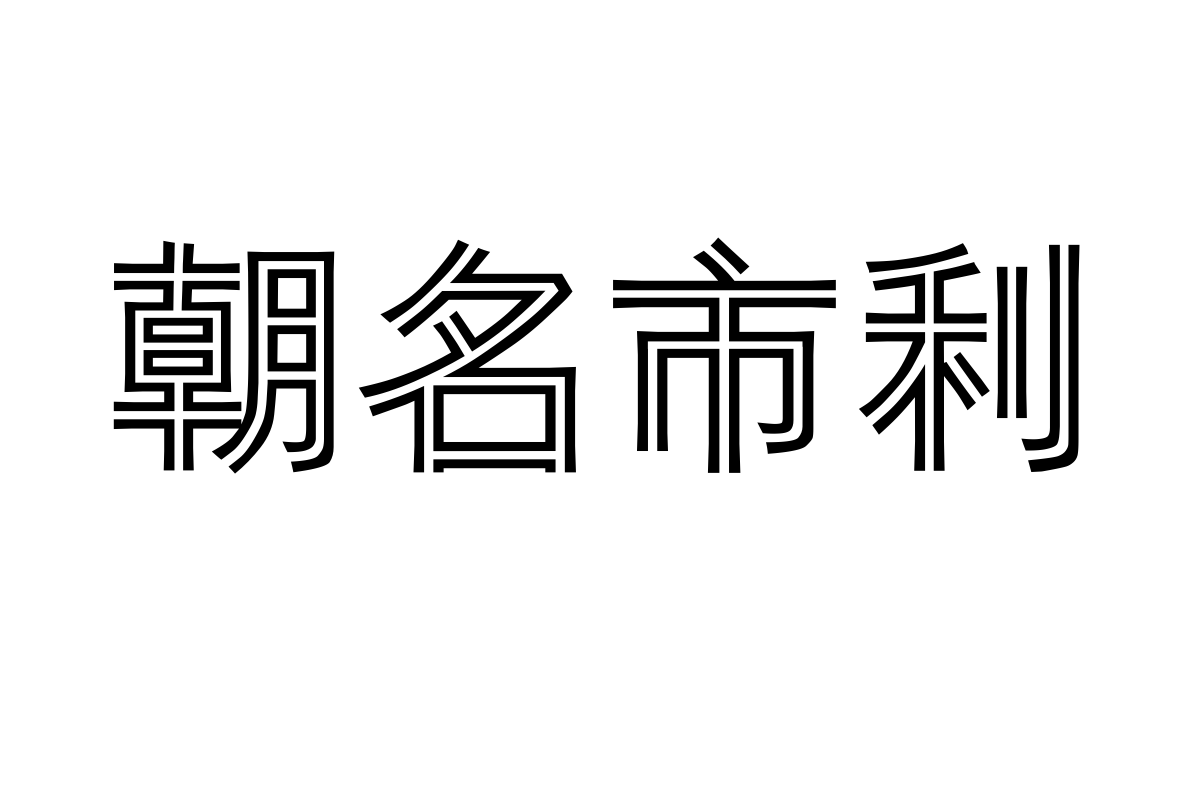
汉仪双线体简是一款具有独特风格的中文字体,由汉仪公司设计。这款字体采用了双线结构,笔画流畅,字形美观大方,适合用于各种印刷品、广告、包装等领域。其特点包括:
1. 线条清晰:汉仪双线体简的线条清晰,笔画流畅,给人一种简洁明快的感觉。
2. 字形美观:该字体的字形美观大方,适合用于各种印刷品、广告、包装等领域。
3. 适应性强:汉仪双线体简适用于各种印刷品、广告、包装等领域,具有良好的适应性。
4. 风格独特:汉仪双线体简具有独特的风格,与其他常见的中文字体相比,更加突出个性。
总之,汉仪双线体简是一款具有独特风格的中文字体,适合用于各种印刷品、广告、包装等领域。